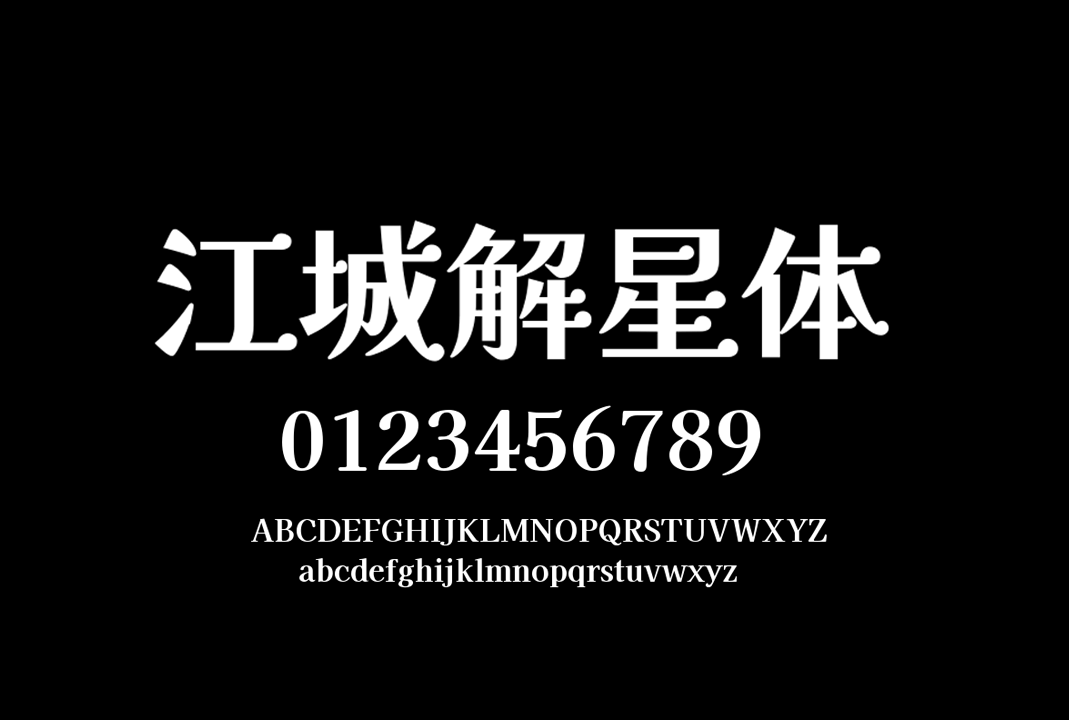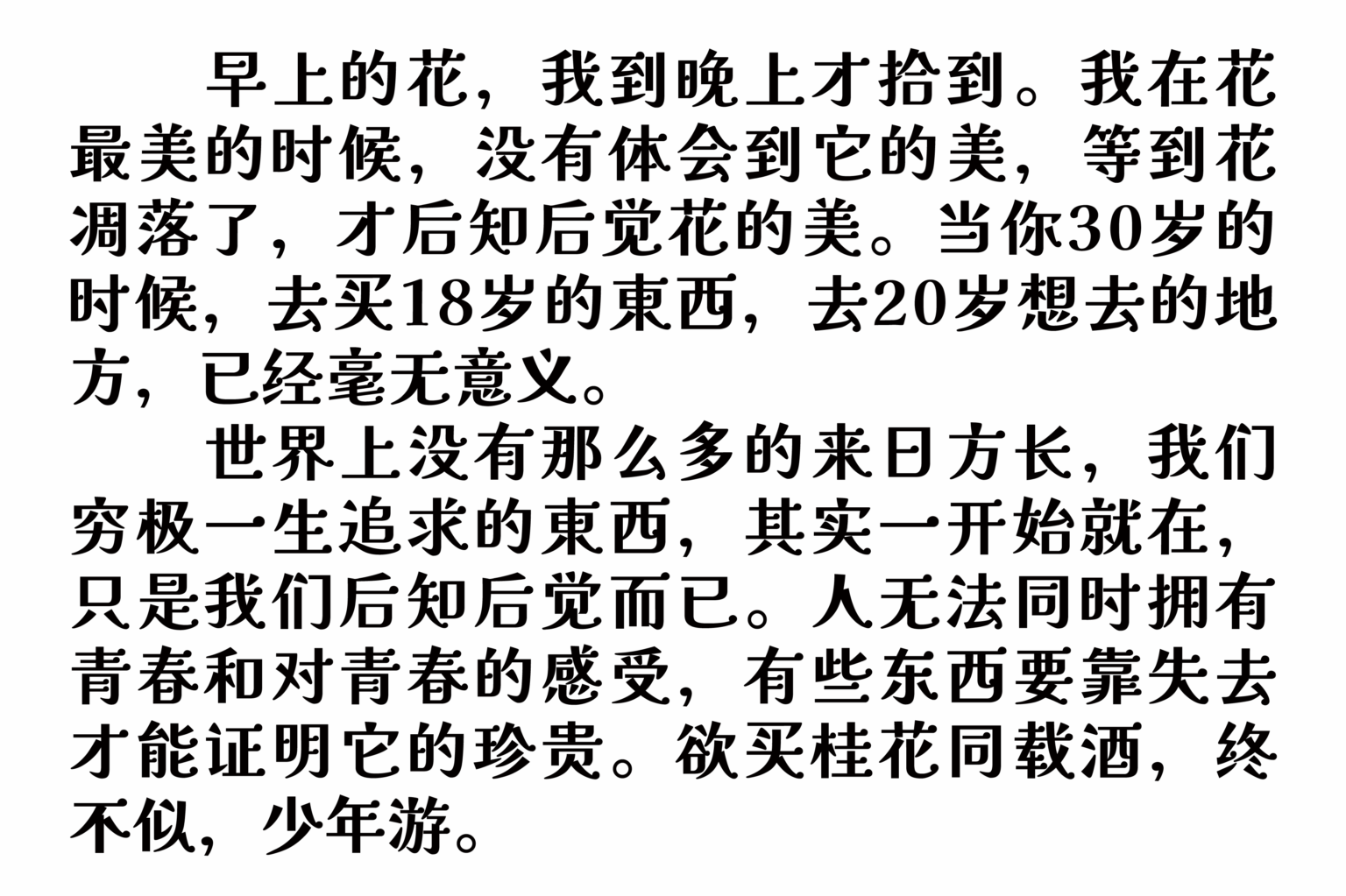
江城解星体是基于日本开源字体解星体改造的一款免费商用中文字体。由于原字体制作的汉字部分主要是依据日本的 JIS 水准,所以在中国大陆使用会有很多缺字少字的情况,于是设计师刘鹏(@设裂星辰)对其简体部分进行了补充。
江城解星体最大的特点就是在横向笔画右侧的末端和笔画转折处添加了圆型衬线,一个“星型” 装饰的小圆点,给人一种可爱、俏皮的视觉感受,所以特别适合应用于美妆、文创、动漫、餐饮(如甜品店、咖啡馆)、儿童教育、出版(绘本、艺术书籍)以及服装设计(童装、女装)等行业。
目前江城解星体已更新 v1.3 版本,补全了现代汉语通用字表(3500字常用汉字表)及部分扩展字,简体字总数达 6424 个,基本可以满足日常使用需求。